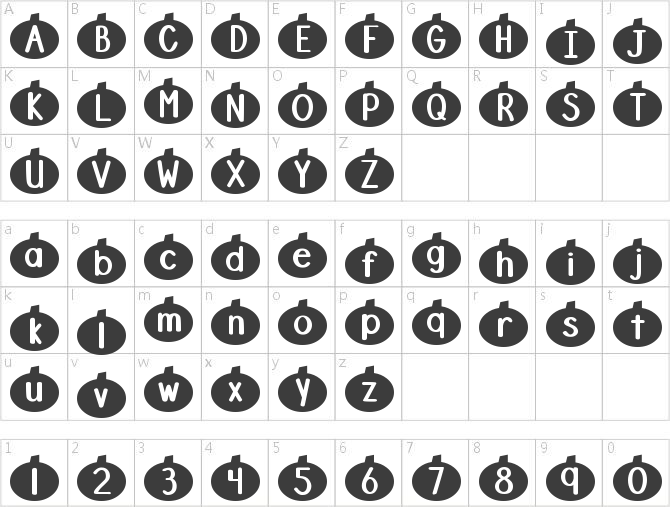
DJB Linus' Pumpkin 詳情頁(yè)
DJB Linus' Pumpkin字體字庫(kù)是一款讓人賞心悅目、百看不厭的英文字體,適合各類(lèi)廣告和產(chǎn)品包裝設(shè)計(jì)應(yīng)用,字體大小0.02MB,格式為ttf字體,上傳用戶(hù)是雅迪,作者/版權(quán)方為未知